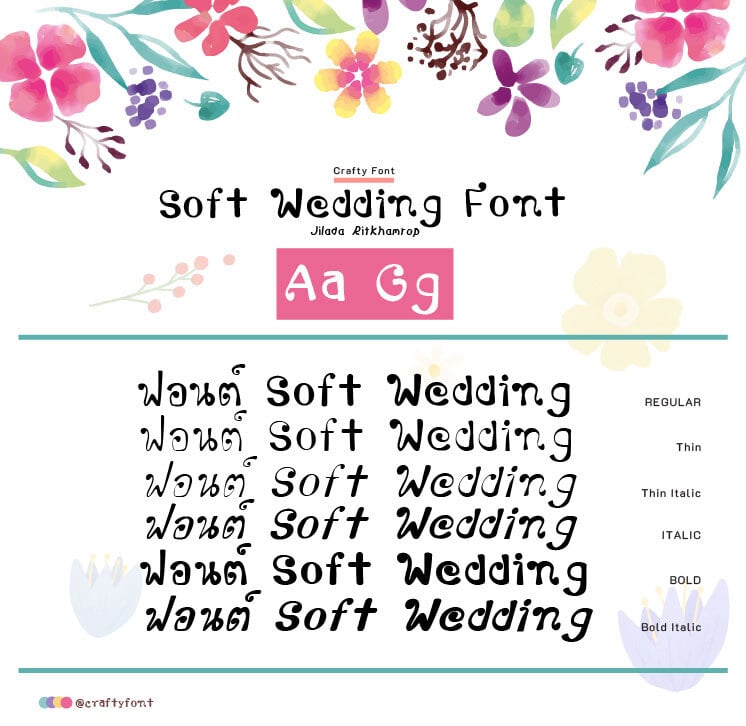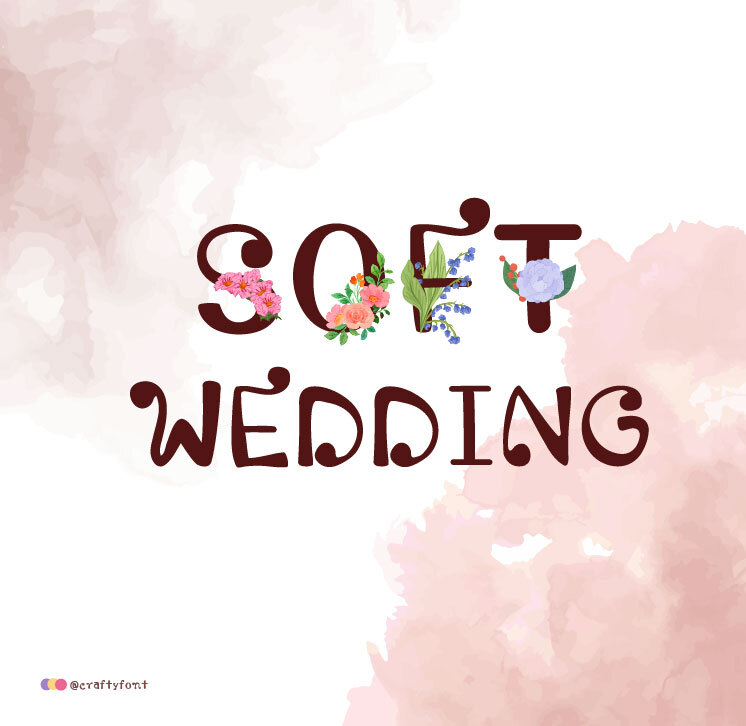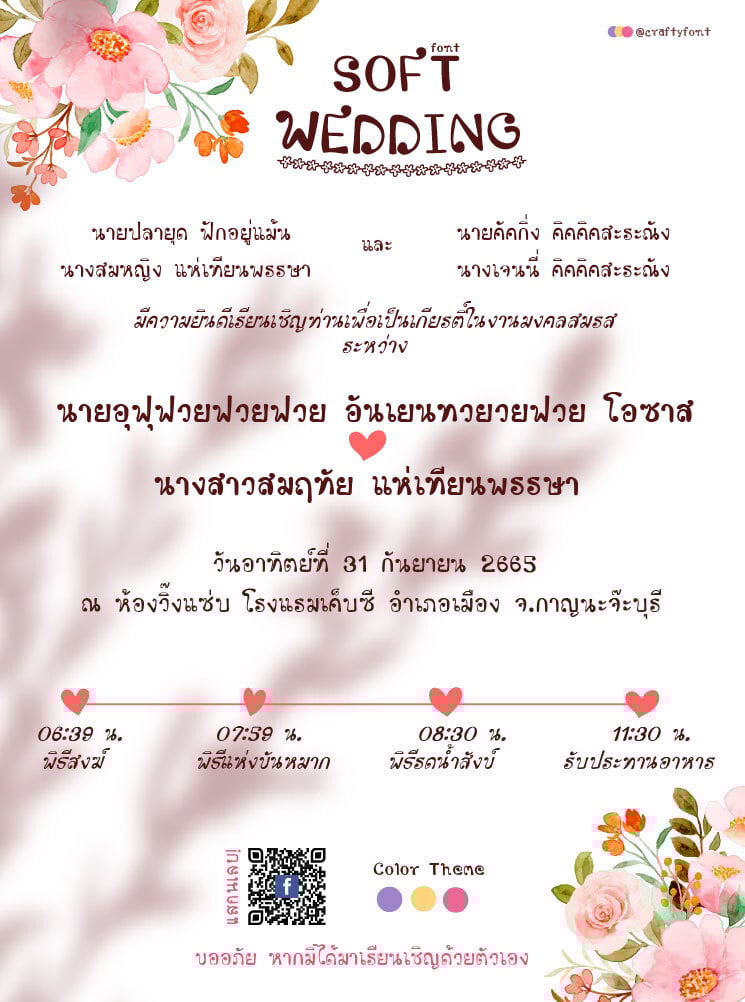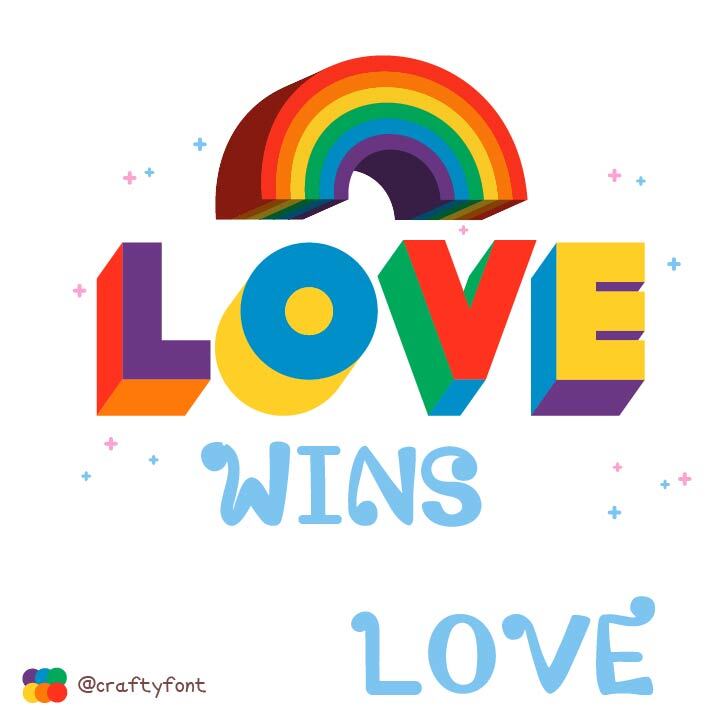
Soft Wedding Font (ฟอนต์ซอฟต์เวดดิ้ง)
ฟอนต์หวานๆ เส้นพลิ้วๆ เหมือนอยู่ท่ามกลางหมู่ดอกไม้ อากาศสบายๆ 22 องศา 😄
ฟอนต์ Soft Wedding ออกแบบมาให้ใช้บนการ์ดงานแต่งงานของเพื่อนเค้าเอง ไม่รู้จะให้อะไร ก็ทำฟอนต์ให้ซะเลย 🥰